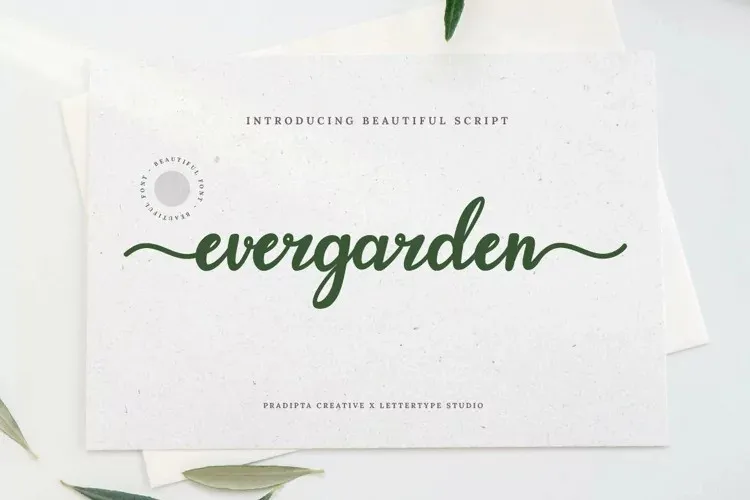
Evergarden Font
A Evergarden Font é uma elegante tipografia script fabricada pela Pradipta Creative, perfeita para projetos que valorizam temas femininos e delicados. Seu design refinado, moderno e sofisticado fazê-la se destacar num contexto onde a elegância tem grande relevância. A fonte permite um uso criativo através das ligaturas e alternativas estilísticas, oferecendo-lhe a oportunidade de personalizar suas próprias letras. Adicione-a a suas ideias mais arrojadas e observe como ela as torna vivas e memoráveis. Ideal para aqueles que buscam uma fonte única para projetos onde o cuidado e delicadeza são fundamentais.